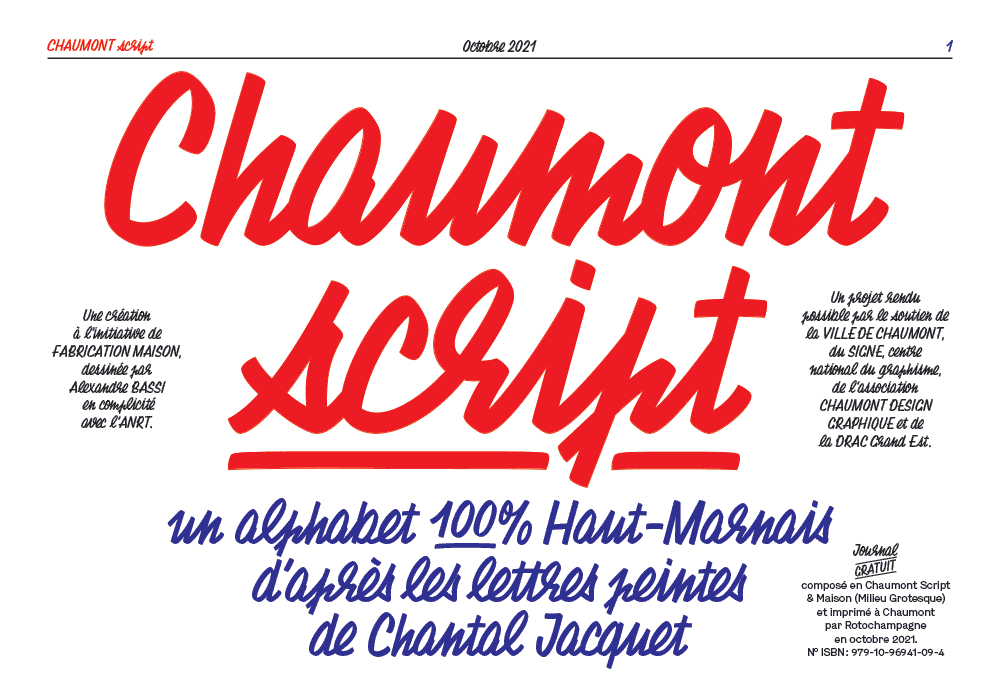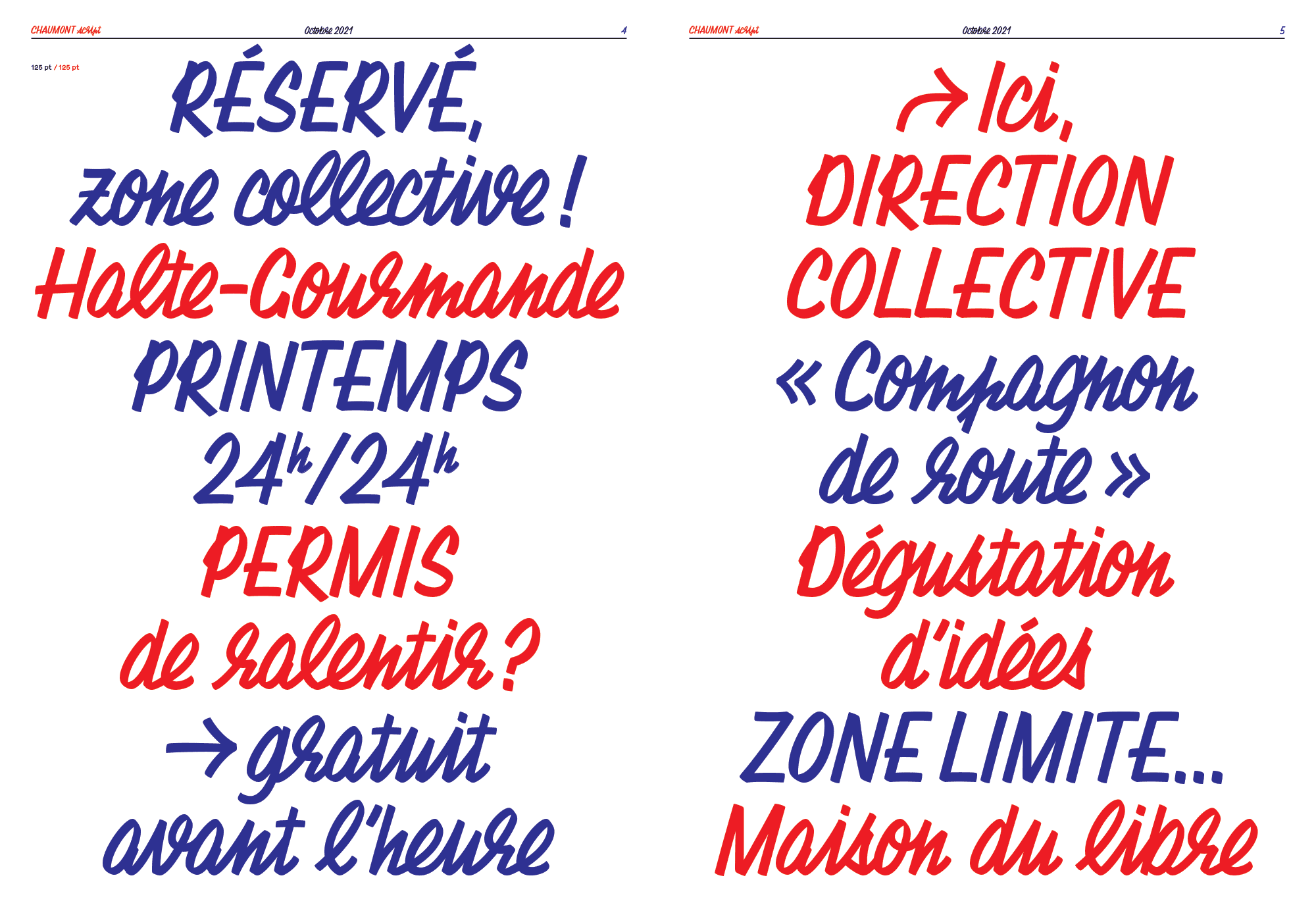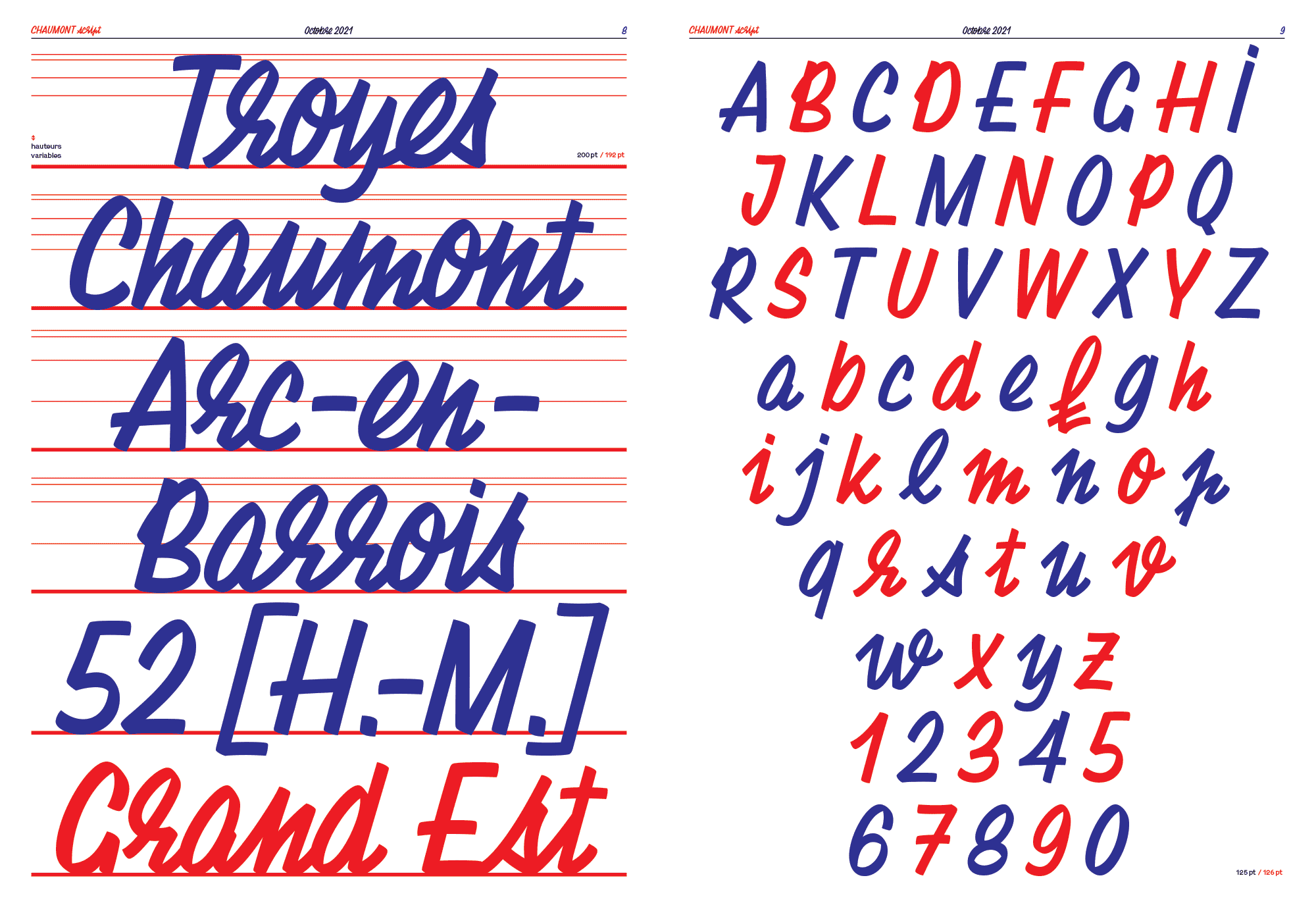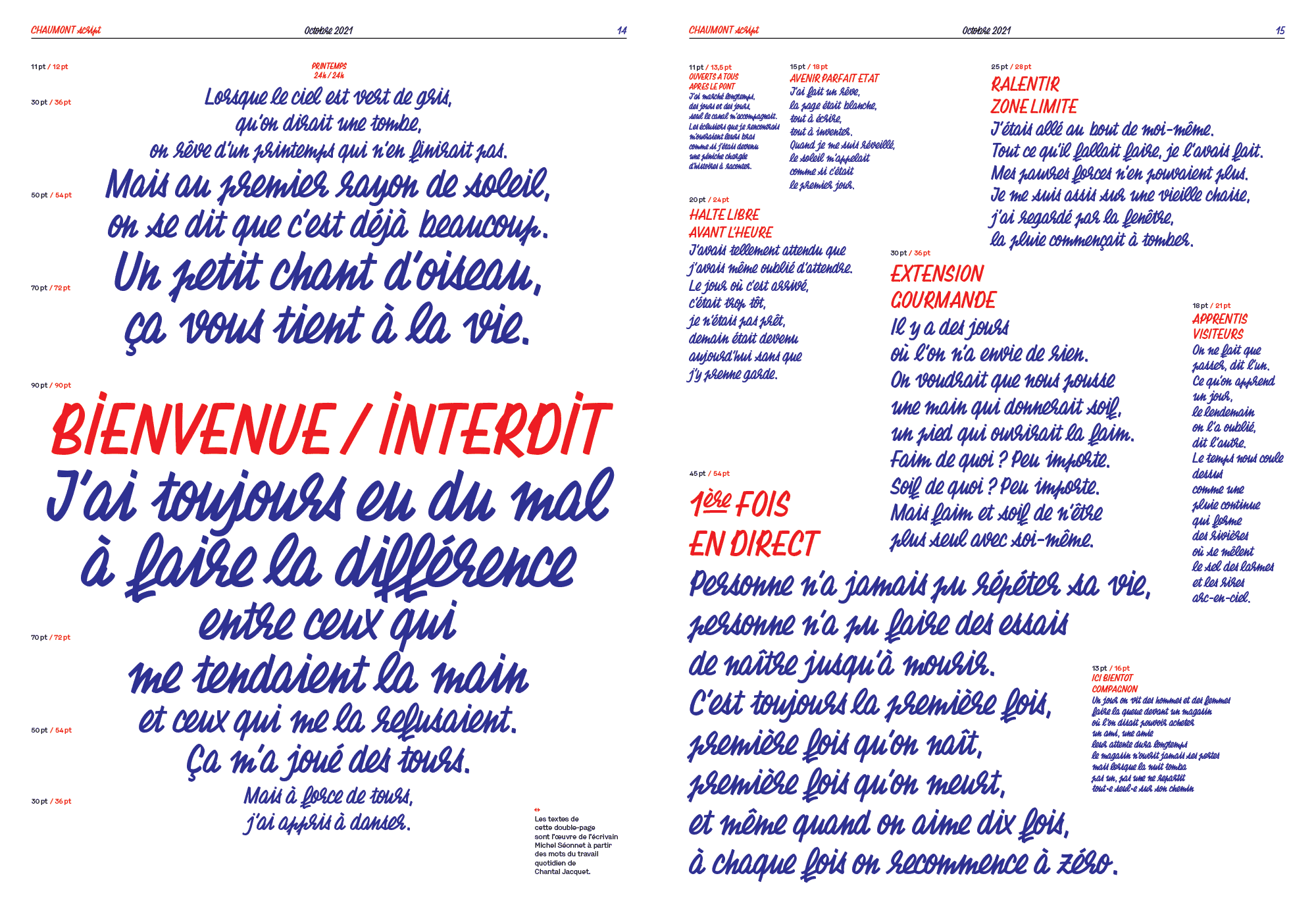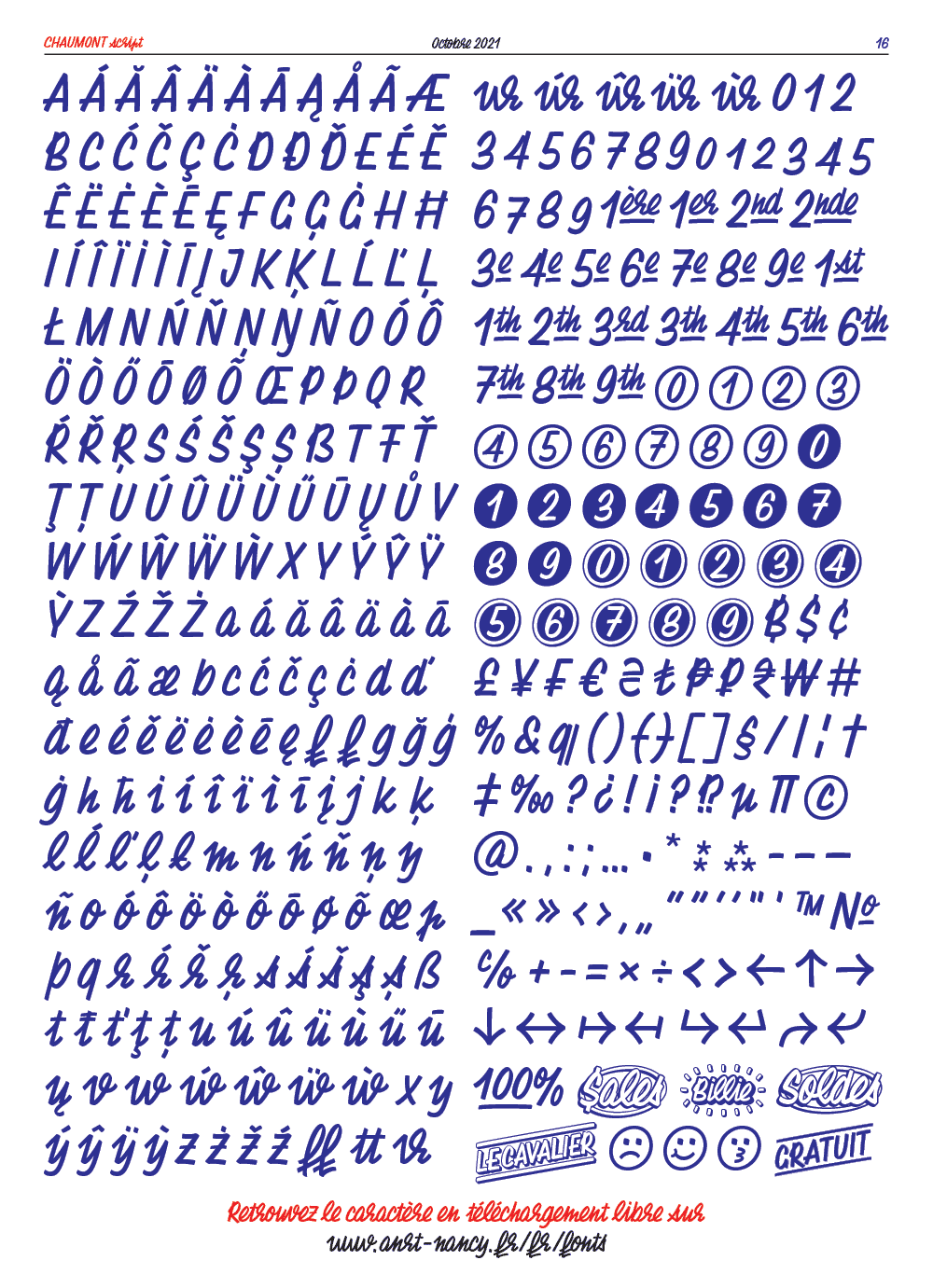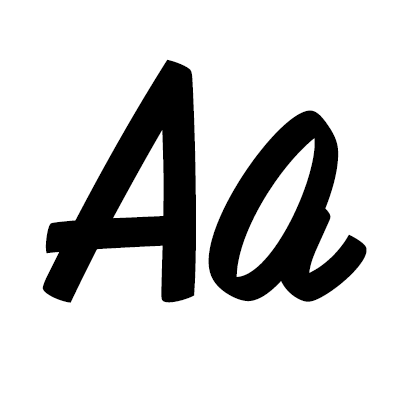
Die Chaumont Script basiert auf dem Schriftstil des französischen Schildermalers Chantal Jacquet. Durch unzählige Varianten und Ligaturen ist der Stil als digitaler Font nutzbar gemacht worden. Die Schrift mit über 2000 Glyphen erschien unter der Open Font License und als Beta-Version bei Atelier National de Recherche Typographique.